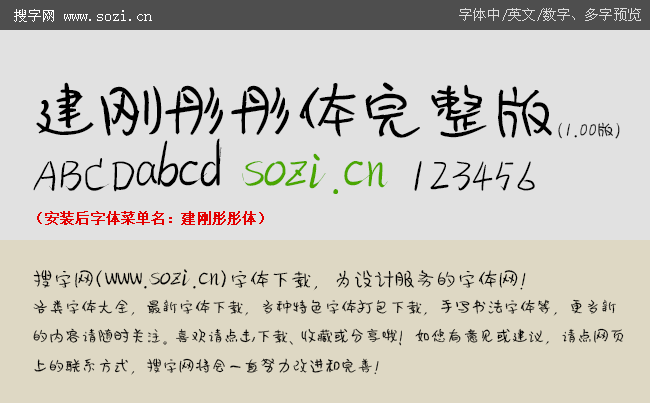
建剛彤彤體完整版
搜字網(wǎng)提供一款建剛彤彤體完整版中文藝術(shù)字體下載,建剛彤彤體是一款帶有手寫風格的中文藝術(shù)字體,線條卡通感很強,整體效果非常不錯,可以應(yīng)用于廣告設(shè)計、名片設(shè)計、包裝印刷、產(chǎn)品設(shè)計等方面,有喜歡的朋友可免費下載收藏。